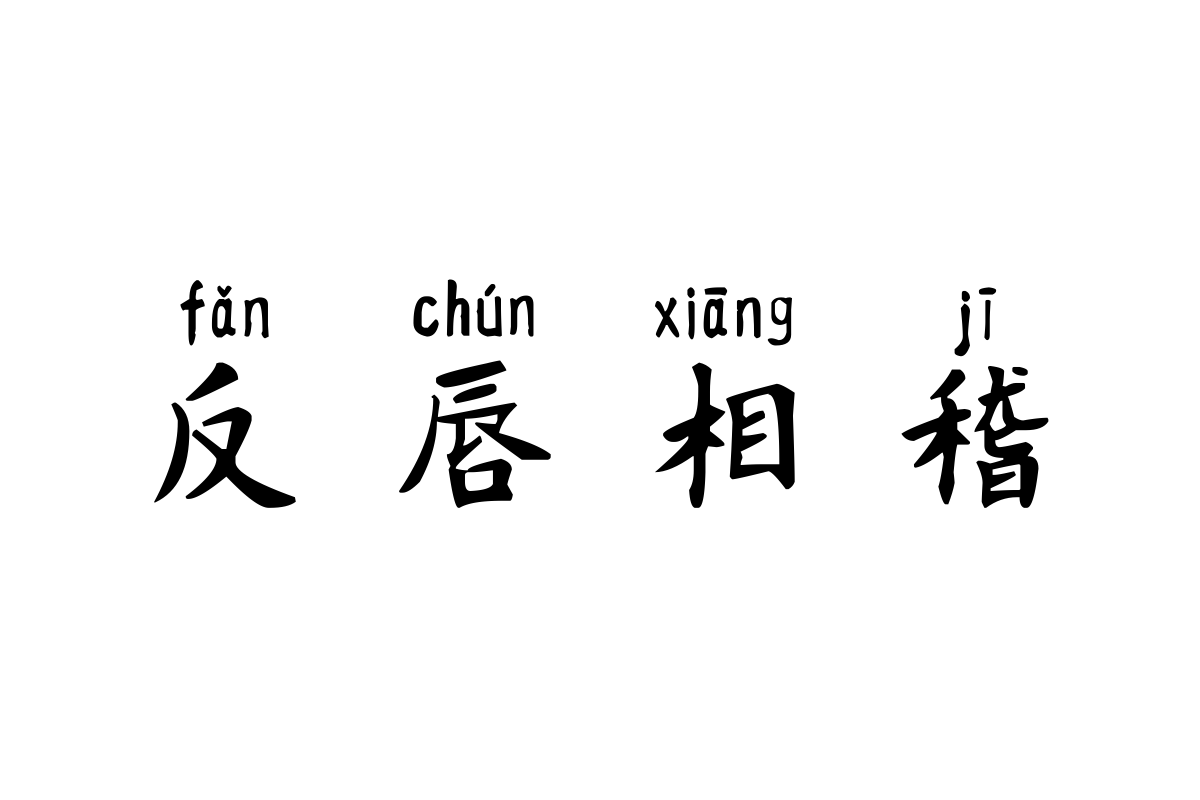
汉标榜样毛笔字体是一种具有独特风格和特色的中文字体。这种字体的特点是笔画流畅,结构紧凑,给人一种优雅、大气的感觉。它适合用于标题、正文、广告等场合,能够很好地表达出文字的美感和内涵。
汉标榜样毛笔字体的特点如下:
1. 笔画流畅:汉标榜样毛笔字体的笔画流畅自然,没有过多的装饰性线条,使得整个字体看起来更加简洁、大方。
2. 结构紧凑:这种字体的结构紧凑,每个字的笔画分布均匀,使得整个字体看起来更加整齐、有序。
3. 优雅大气:汉标榜样毛笔字体给人一种优雅、大气的感觉,适合用于各种正式场合的宣传材料、海报等。
4. 易于阅读:汉标榜样毛笔字体的笔画粗细适中,既不过于粗犷也不过于细长,使得整个字体易于阅读,提高了信息的传递效率。
总之,汉标榜样毛笔字体是一种具有独特风格和特色的中文字体,适合用于各种正式场合的宣传材料、海报等。